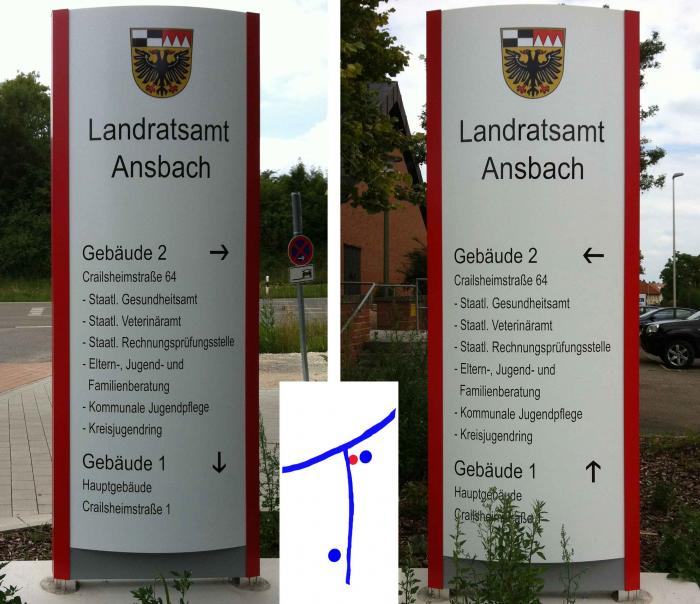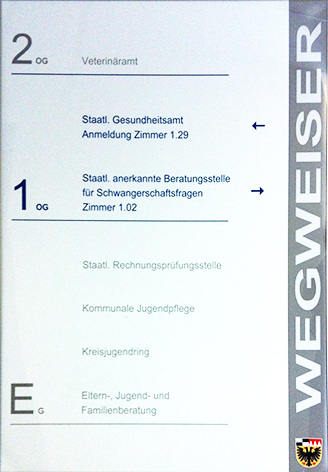
Das Landratsamt in Ansbach hat im Februar ein neues, zusätzliches Gebäude bezogen, in derselben Straße, vielleicht knapp dreihundert Meter entfernt vom Hauptgebäude in derselben Straße. An der Einfahrt wurde ein großes Hinweisschild angebracht, das mich nicht überzeugt:
Die Skizze zwischen den Fotos zeigt die Verhältnisse: Der rote Punkt markiert den Standort des Wegweisers, der blaue Punkt gleich daneben stellt das neue Gebäude 2 dar und der andere blaue Punkt ist das Hauptgebäude (Gebäude 1). Wenn man vom Hauptgebäude kommt, sieht man also das Schild auf dem linken Foto, das rechte Foto zeigt die Rückseite.
Auf mich wirken die Pfeile, einmal nach oben und einmal nach unten gerichtet, nicht besonders glücklich, schließlich geht es zum Gebäude 1 weder abwärts noch aufwärts. Mir fällt aber auch keine bessere Lösung ein. Hat jemand eine Idee, wie man das gut lösen könnte (auch wenn nicht zu erwarten ist, dass das Landratsamt an den Schildern noch etwas ändert)?
Es ist zumindest die übliche Form. Wenn man an einem ebenerdigen Ort (also keine Treppenhäuser, Rolltreppen etc.) auf einer vertikalen Darstellungsfläche (Wand/Info-Säule etc.) »zurück« und »geradeaus« darstellen will, dann nimmt man »Pfeil nach unten« und »Pfeil nach oben«.
Das deutsche Verkehrsleitsystem setzt das zum Beispiel auch (in Gegensatz zu anderen Ländern) konsequent um. »Pfeil nach oben« ist immer »geradeaus«, egal ob der Pfeil neben oder über der Straße angebracht ist. Sehr gut!
Für komplizierte Fälle schlage ich ja 3D-Pfeile vor:
Aber eine feste Konvention ist das freilich nicht und es gibt natürlich auch kaum Fonts, die das integriert haben und somit leicht für die Anwendung zur Verfügung stellen.
abgesehen von den pfeilen ist es ganz übel, wäre die typo kleiner, dafür ein tick kräftiger und mehr in augen höhe aber so? auf dem einem wächst es jetzt schon am boden zu. :hammer:
Ist eh schon viel zu viel Weißraum auf dem Schild. Ich hätte da noch mindestens fünf bis sieben Katzenfoto untergebracht :hammer:
Die Hoch-/Runterpfeile würde ich allerdings – trotz des vielen Weißraumes ;-) – verstehen. Eben weil man das so gewohnt ist. Wo die deutschen Schilder nicht ganz konsequent sind, sind Halte- und Parkverbotsschilder, da sind die Pfeile nach links und rechts, auf wenn dass Schild 90° gegen die Fahrbahn gedreht ist, aber hier ist es vielleicht auch schwer, das umzusetzen …  :-?
dann hätte man doch die zur Verfügung stehende Fläche nicht ganz ausgenutzt!
Die Schilder im Haus sind ja noch schlimmer:
Nachdem hier die ursprünglichen Schilder nachträglich ausgewechselt werden mussten (irgendjemand hatte einen falschen Träger montiert), hatte ich Gelegenheit, der zuständigen »Hauptverwaltung« ein paar Hinweise zu geben. Umgesetzt wurde fast nichts. Die Beschriftung des Wegweisers mit »Wegweiser«, mit der verzerrten Schrift, musste offensichtlich bleiben, da half nicht einmal meine Drohung mit der Typo-Hölle. Vielleicht hat jemand gemeint, wenn das nicht draufsteht, weiß kein Besucher, was es sein soll. Das glaube ich aber fast nicht, weil wenn es wirklich wichtig wäre, dürfte man es ja nicht vertikal schreiben, sodass sich die Besucher den Hals verrenken müssen. Vermutlich sah man diesen Schriftzug einfach als Verzierung.
Ich vermute, dass die Optiker am Ort unterstützt werden sollten.
Wobei mir die Verwendung des "OG" als quasi Punkt schon wieder gefällt :-)